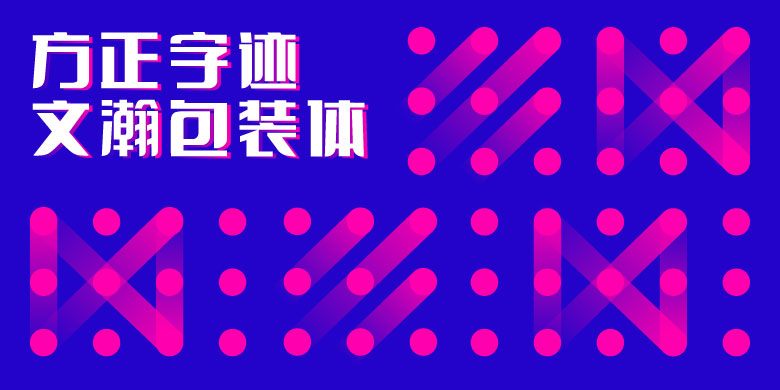
方正字迹-文瀚包装体
字体介绍:
目前,行业专属字体很少,比如包装行业基本涵盖各行各业,建筑业占全国半壁江山,传媒行业,图书、报纸、电视、网络等包括诸多行业都应该有各自不同的风格各异的字体。缘于此,分别试设计出“包装体” 、“建筑字体”、“传媒字体”“装饰字体”等和其它美术字体。<BR>方正字迹-文瀚包装体源于过去作者的专业,在食品研究所进行包装设计工作,对包装设计有挥之不去的情结。故立意用绿色叶瓣为基本形状,在字体的结构上象征叶瓣修饰扣处理,寓意为大众能亨用放心的绿色食品。文瀚包装体是一款实用的美术字体,结字为左圆右方,方圆结合,雍容华丽,醒目大方,适用于海报,广告,产品包装的字体。